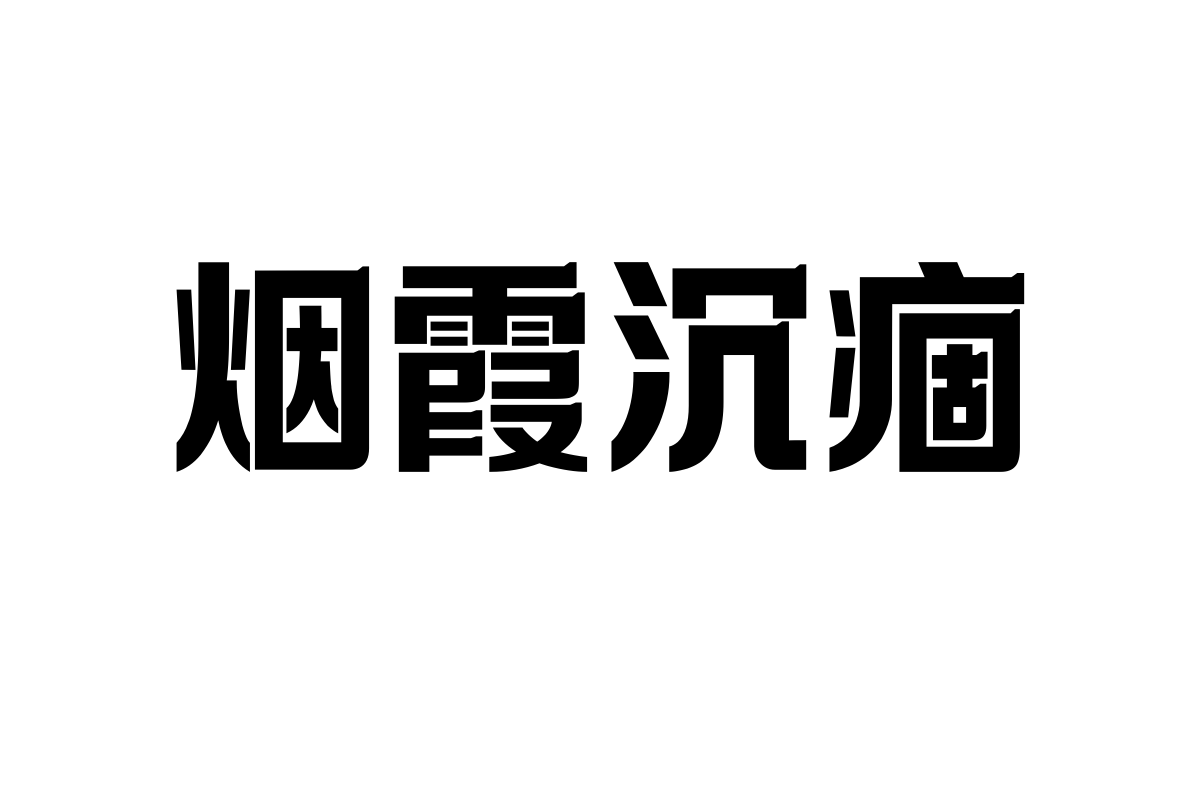
上首梦黑体是一款无衬线字体,具有现代感和强烈的视觉冲击力。它由上海上首文化传媒有限公司设计。这款字体的笔画流畅,结构简洁,易于阅读和书写。它的字形特点包括:
1. 字形简洁:上首梦黑体的字形线条清晰,没有过多的装饰,使得整体看起来更加简洁明了。
2. 结构紧凑:上首梦黑体的每个字符都紧密地排列在一起,使得整个字体看起来非常紧凑。
3. 易读性强:由于其结构简单,笔画流畅,因此上首梦黑体在阅读时非常易读,不容易出现误读的情况。
4. 适应性强:上首梦黑体适用于各种印刷媒介,如报纸、杂志、书籍等,无论是大字还是小字,都能保持清晰的视觉效果。
5. 通用性高:上首梦黑体不仅适用于中文排版,也适用于其他语言的排版,具有较高的通用性。